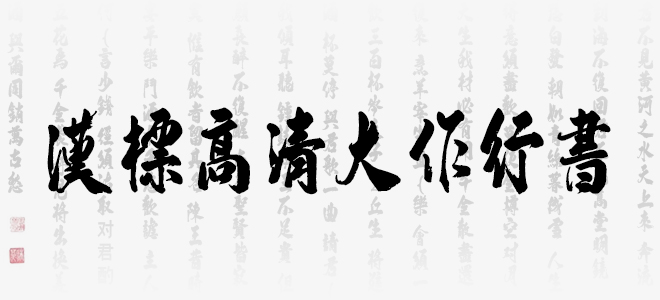
汉标高清大作行书是一款带有书法味道的纯手写高清大字体,由书法家历时半年精致书写,笔画中保留了过多的笔锋,字体厚重、饱满。因为是纯手写的原因,它独特的气质更与其他字体不同,看似统一,其实各有各的味道,每个字都可以独具风情。字由字在,大到自然,便是对它最好的诠释。欢迎喜欢汉标高清大作行书字体的朋友前来下载使用。
汉标高清大作行书